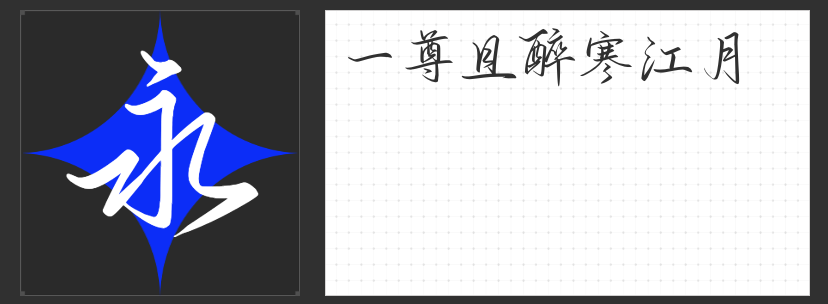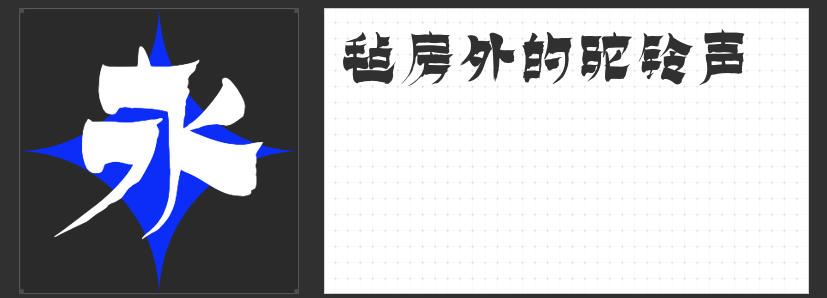
国潮风起时,四款匠心字体赋能广告设计新美学
在国潮文化复兴的浪潮中,广告设计正以更具东方韵味的视觉语言重塑品牌魅力。当传统书法与现代设计碰撞,四款兼具艺术性与实用性的匠心字体脱颖而出,以独特的笔墨哲学为广告创意注入灵魂。
一、造字侠永刚漆书简繁
这款以漆书为灵感的毛笔手书字体,以厚重的笔画构建出如青铜器铭文般的庄重感。其撇捺舒展如刀刻斧凿,转折处暗藏篆隶的古拙意趣,在保持框架醒目的同时,通过灵动的笔触平衡了字体的肃穆气质。无论是作为包装标题的视觉核心,还是广告画面中的文化符号,都能以统一而富有张力的风格传递品牌底蕴。
二、造字侠仗剑简繁 传神
字形如侠客仗剑而行,这款书法字体以夸张的折笔与提钩演绎出江湖豪情。高度折叠的笔画结构既保留了书法的写意性,又通过几何化的处理增强了现代感。在运动品牌或武侠主题的广告中,其干净利落的笔锋可瞬间点燃画面张力,让文字本身成为传递品牌态度的视觉武器。
三、造字侠侠义简繁
圆转代方折的笔画创新,赋予这款字体如行云流水般的韵律感。勾挑牵丝的细节处理既延续了草书的洒脱,又通过适度的收放控制确保了辨识度。在需要营造强烈情绪张力的广告场景中,其大气磅礴的笔势可瞬间抓住观众视线,尤其适合文化创意类品牌的视觉表达。
四、字圈也字醉寒江行草
这款行草字体以"易识性"为设计核心,在保留书法个性的同时优化笔迹连贯性。起承转合间既有文人墨客的从容气度,又暗含现代设计的理性秩序。当应用于高端消费品的广告文案时,其张弛有度的笔法能完美平衡商业信息与艺术美感,让文字成为传递品牌格调的媒介。
在国潮设计从"形似"向"神似"进阶的今天,这四款字体以不同的笔墨哲学,为广告创意提供了更丰富的文化表达维度。它们不仅是视觉工具,更是连接传统与现代的美学桥梁,助力品牌在文化浪潮中书写属于自己的东方叙事。